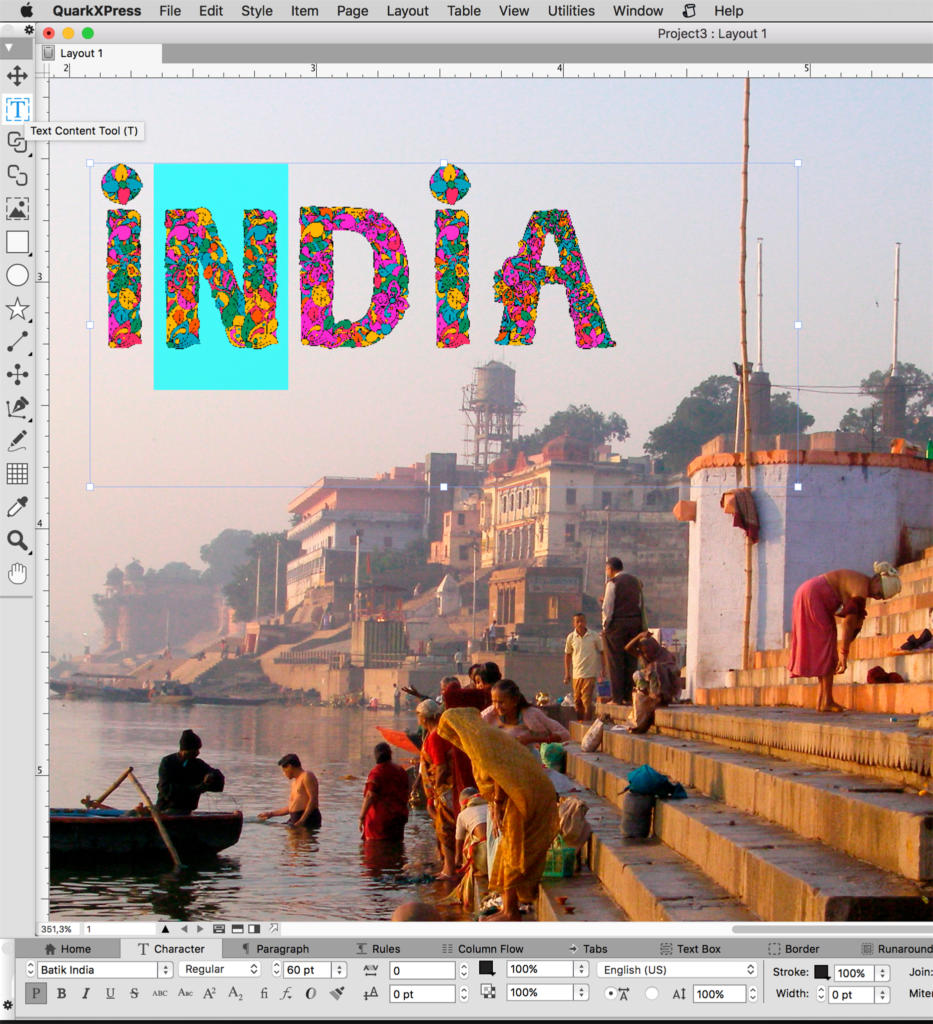
Vektorbasierte Schrifteffekte musste man bisher meistens in einem Grafikprogramm wie Adobe Illustrator, Corel Draw oder Affinity Designer erstellen. Für pixelbasierte Texteffekte gibt es Adobe Photoshop, Corel Painter oder Affinity Foto. Doch eine typografische Gestaltung in Zeichenprogrammen ist aufwendig und oft mangelt es an Flexibilität im Arbeitsprozess. Änderungen sind umständlich, zeitintensiv und man ist stets an das Programm gebunden, mit dem die Texteffekte ursprünglich erstellt wurden.
Die farbigen Effekte
Mittlerweile geht es aber auch viel komfortabler: Eine entsprechende Schriftdatei vorausgesetzt, tippt man die Color Fonts beziehungsweise den Effekt ganz einfach ins Layoutprogramm ein.
Möglich macht es „OpenType-SVG“, ein Schriftartenformat, mit dem Buchstaben in Form von skalierbaren Vektorgrafiken (SVG) dargestellt werden. Dadurch wird die Anzeige mehrerer Farben in einem Buchstaben möglich.
Farbschriftarten sind dabei nicht neu, sie konnten schon früher realisiert werden, indem zwei oder mehr entsprechende Schriftarten in verschiedenen Farben übereinander gedruckt wurden. Jede Schrift hat Bereiche weggeschnitten, um die Farbe der darunterliegenden Schrift freizugeben oder zu überlappen.
Color Fonts sind OpenType-SVG-Schriften, welche die Anzeige mehrerer Farben in einem Buchstaben ermöglicht.
OpenType-Schriften
Der Color-Fonts-Schrift-„Container“ OpenType ist ebenfalls nicht neu. Die Verbreitung von Desktop-Publishing in den 1990er-Jahren stellte Schriften vor neue Herausforderungen. Diese mussten zunehmend plattformunabhängig sein und es mussten Sprachen mit einem größeren Zeicheninventar als ein lateinischer Zeichensatz integriert werden. So entwickelte Microsoft im Jahre 1996 zusammen mit Adobe das Fontformat OpenType. Vom Jahre 2000 an wurde dann eine größere Anzahl OpenType-Schriften auf den Markt gebracht. Diese waren nicht bloß plattformunabhängig, sondern wiesen auch erweiterte typografische Fähigkeiten auf. Das war neu, denn die anderen bekannten Schriftformate wie TrueType- und PostScript-Fonts konnten lediglich 256 Zeichen in einer Schriftdatei verwenden. OpenType erweiterte die bis dahin geltende Grenze von 256 adressierbaren Zeichen pro Schrift. Das wiederum nutzten die Schrifthersteller für erweiterte typografische Möglichkeiten mit Varianten von Buchstaben und Zeichen oder eine umfangreichere Sprachunterstützung.
Dennoch hat sich die Typografie seit der Einführung von Open-Type-Schriften nicht wesentlich verändert. Es kamen und kommen zwar laufend neue Schriften und Schriftschnitte hinzu. Doch Schrift konnte bloß in einer Farbe getippt werden – mit nachträglicher Änderung der Farbe von einzelnen Zeichen.
Emoji-Symbole als Auslöser
Die Entstehung der nun vorhandenen Farbschriften geht auf das Jahr 2010 zurück. Damals fügte Apple farbenfrohe Emojis zu ihren Programmen hinzu. Die Bildschriftzeichen treten in Form eines Piktogramms auf und werden in SMS und Chats auf Handys und im Internet gerne eingesetzt, um längere Begriffe zu ersetzten oder einfach um Emotionen darzustellen. Die dadurch eingeführte Fähigkeit, mehrfarbige Vektorelemente in einer einzigen Glyphe zu platzieren, ist somit wohl den weit verbreiteten Emoji-Zeichen zu verdanken.
Unterstützung von Color Fonts
Color Fonts basieren auf neuen Formaten wie Apple SBIX und Google CBDT, beide sind herstellergebunden und auf Bitmap (PNG) aufgebaut. Ferner unterstützt Microsoft mit dem auf OpenType basierenden Vektorformat COLR die Farbschriften für verschiedene eigene Lösungen wie DirectWrite oder Direct 2D. Der neue Font wird als OpenType SVG (W3C SVG, OpenType 3) angeboten. Dieses Format enthält sowohl eine Vektor- als auch eine Bitmapdarstellung.
Photoshop CC 2017 war dann auch die erste Anwendung, welche Bitmap-Farbschriften unterstützte; mit dem Release von CC 2018 kamen auch Vektor-Farbschriften hinzu. Volle Unterstützung bietet zurzeit nebst Photoshop CC 2018 nur Illustrator CC 2018 und das ab Mai erhältliche Quark-XPress 2018. QuarkXPress 2018 ist damit die erste Layoutsoftware, die Farbschriftarten, Bitmap und Vektor vollständig unterstützt.
Noch nicht alle Programme unterstützen vollständig die Color Fonts. QuarkXPress 2018 kommt mit dieser neuen Schriftart als erstes Layoutprogramm klar. Für typografische Gestaltungen können diese Schriften sehr sinnvoll sein.
Zwar unterstützt auch InDesign CC 2018 Color Fonts, jedoch bloß auf Basis einer „experimentellen Farbschriftunterstützung“. Adobe nennt dies eine Technologievorschaufunktion, die möglicherweise noch nicht komplett produktionsbereit ist. So soll es zurzeit noch Probleme bei der Ausgabe von Farbschriften in InDesign geben. Affinity Foto und Affinity Designer unterstützen in den aktuellen Versionen keine Color Fonts.
Bei der Verwendung als Web-Fonts kommen im Moment noch nicht alle Browser mit den Color Fonts klar. Die Browser-Unterstützung entwickelt sich zwar weiter, doch zurzeit sind die Farbschriftarten bloß bei Firefox und Microsoft Edge (IE) abbildbar. In Browsern, die keine Unterstützung für Farbschriftzeichen haben, werden diese als normale Monochrom-Glyphen dargestellt. Aktuelle Informationen zur Browserunterstützung finden Sie bei State of Web Type unter OpenType-SVG.
Color Fonts beziehen
Mit Adobe Illustrator CC 2018 wird nebst der Emoji-Schrift der Color Font Trajan Color installiert. Dies ist ein vollwertiger Color Font, welcher wie die normale Trajan bloß Großbuchstaben enthält.